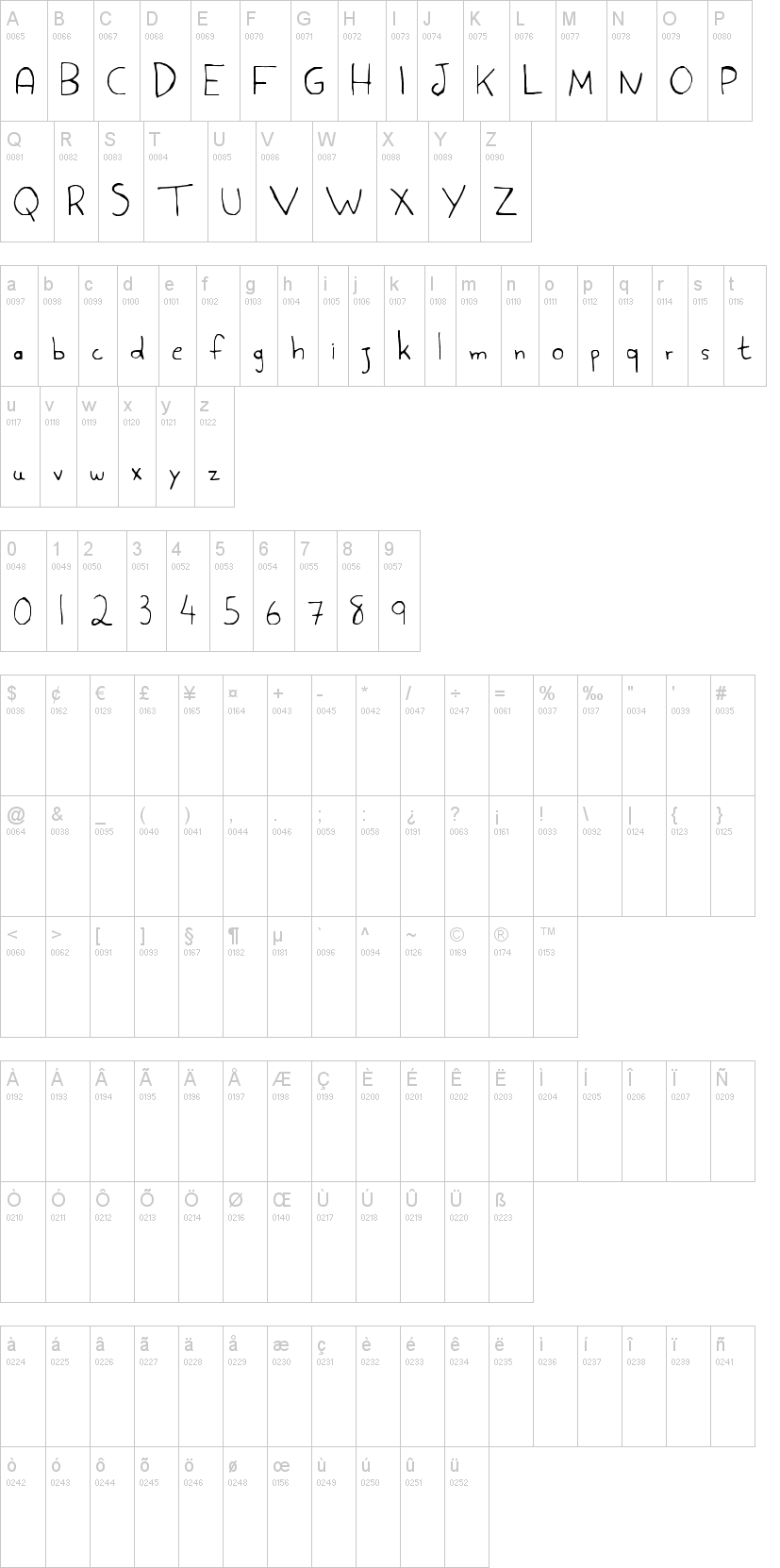
Aspargo 字体是一款基于西班牙语设计的英文字体,它与西班牙语的节奏和风格有着良好的结合。Aspargo 字体的设计灵感来源于西班牙的传统文化,它的字形具有传统的西班牙风格,但又不失现代感。Aspargo 字体的字形特点是圆润而柔和,给人一种温暖而浪漫的感觉,适合用于日常文字排版和品牌设计中。内容介绍
Aspargo是一款非常不错的手写艺术字体,具有很好的视觉感,适合于文化类的宣传设计、商业类品牌的广告和产品包装设计以及个性化文字排版等较多场景。